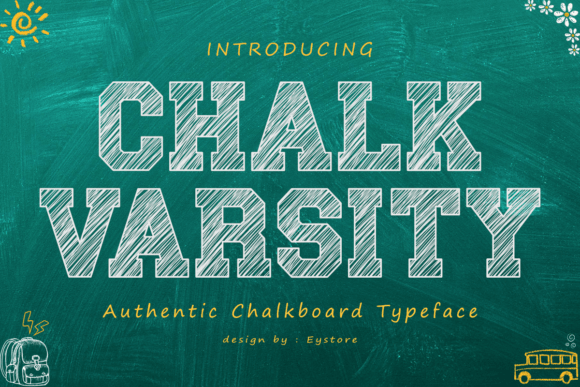
Chalk Varsity
適切なデザイン要素を見つけるのは難しい場合がありますが、Chalk Varsityは作品を即座に引き立てる優れたコレクションを提供します。
精密に作られたChalk Varsityは、クリーンなベクター、滑らかなタイポグラフィ、そして安心のための商用ライセンスを提供します。
POD(オンデマンド印刷)製品、結婚式の招待状、またはソーシャルメディアのグラフィックを作成している場合でも、Chalk Varsityは理想的です。